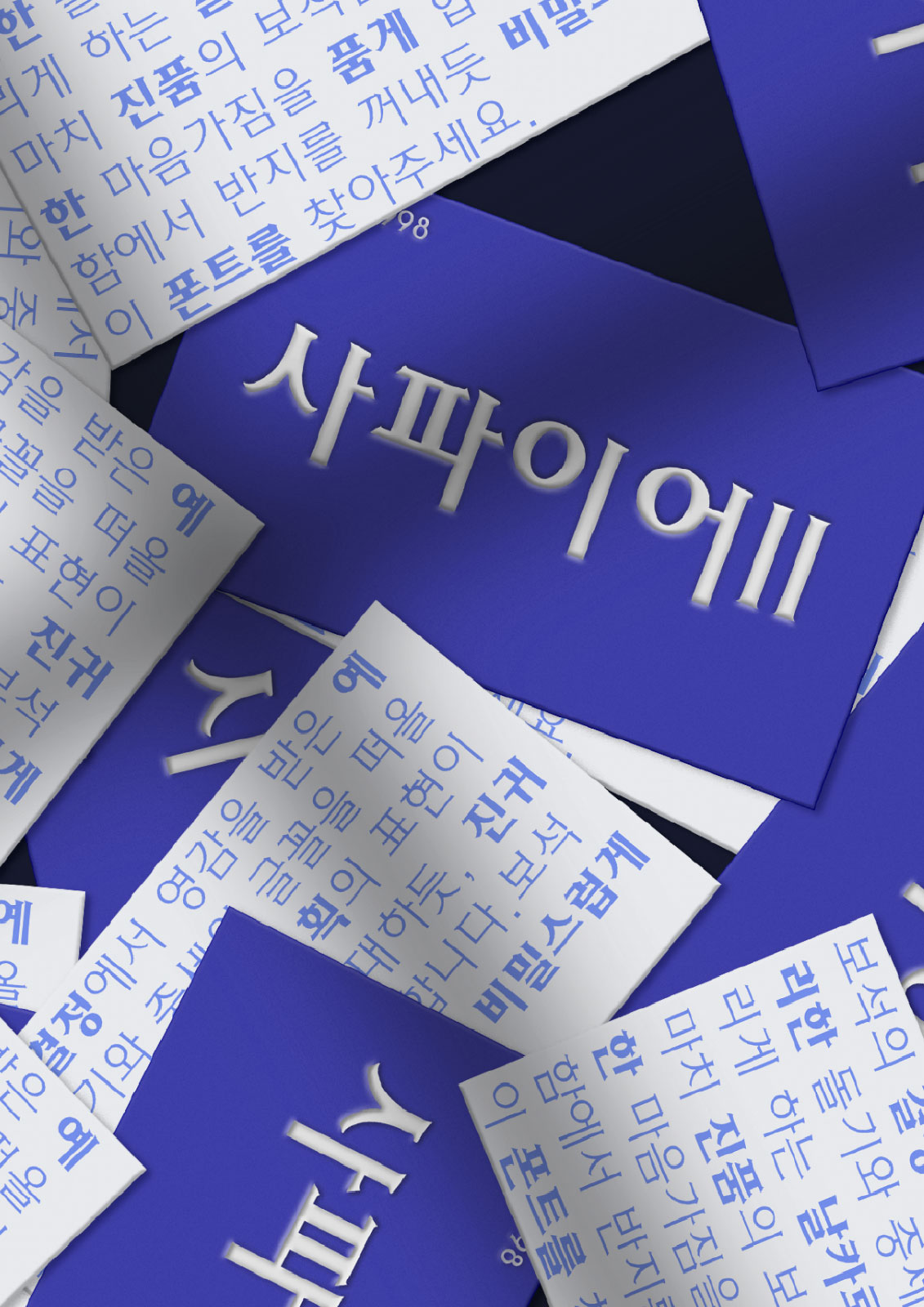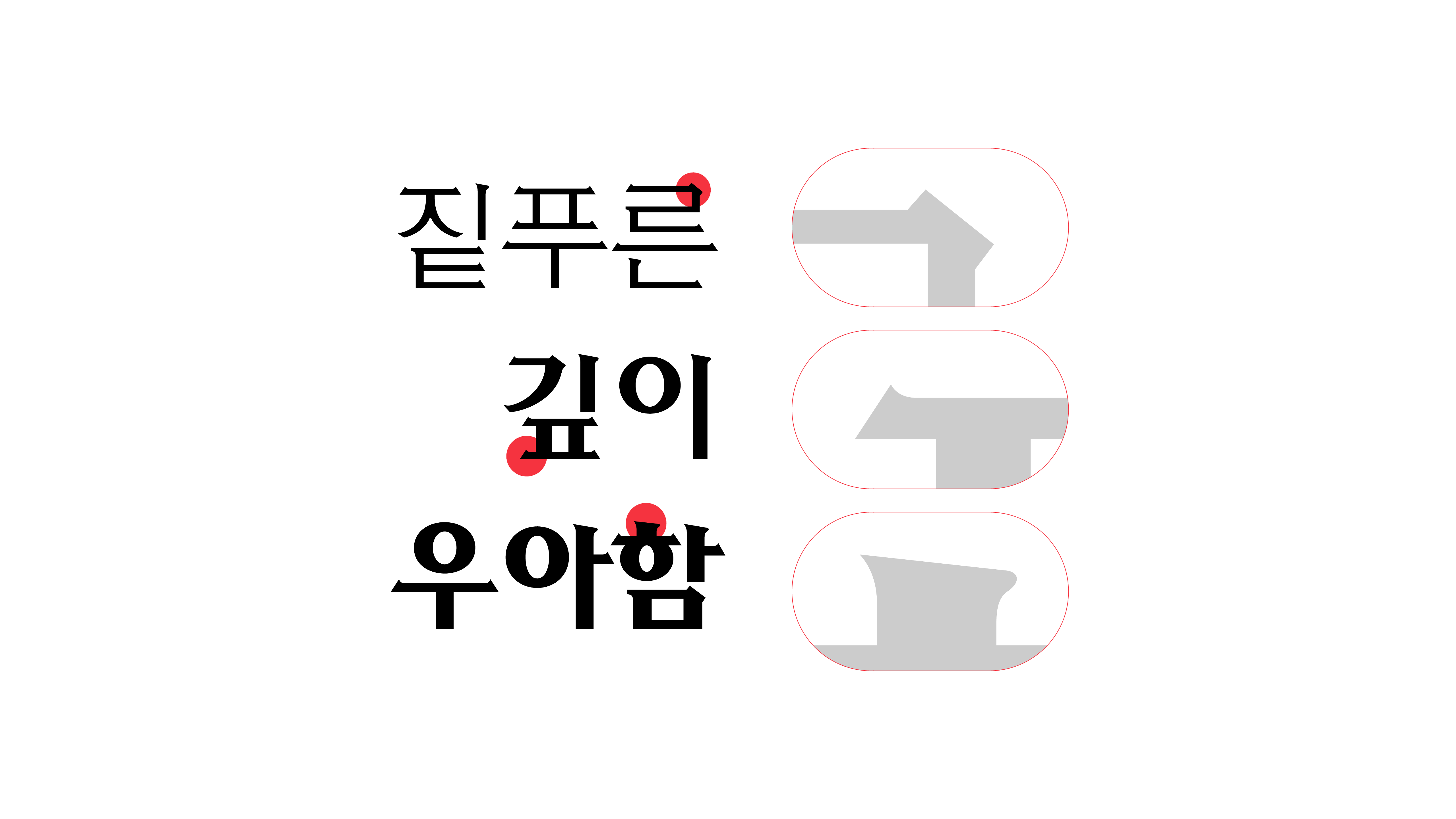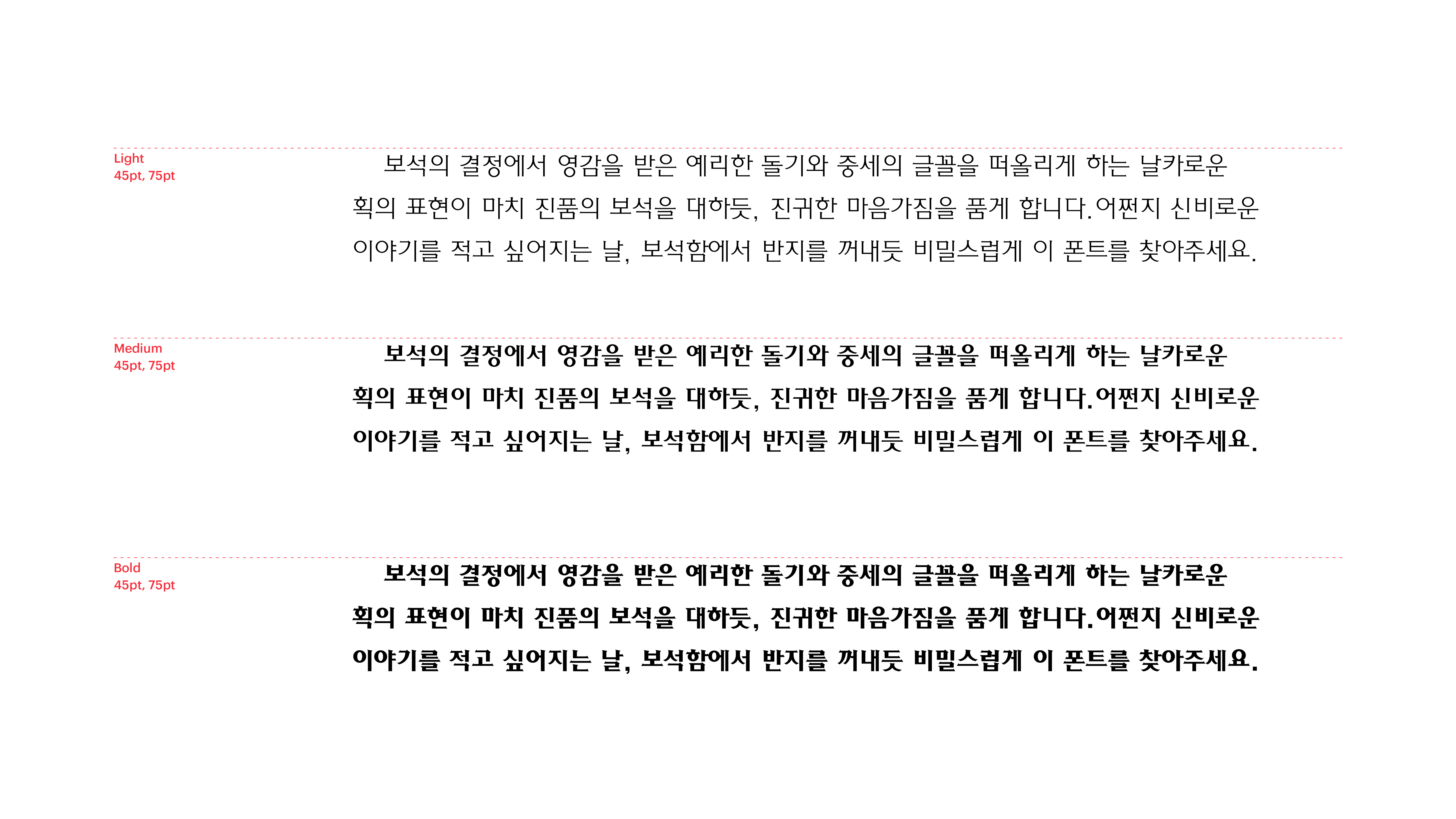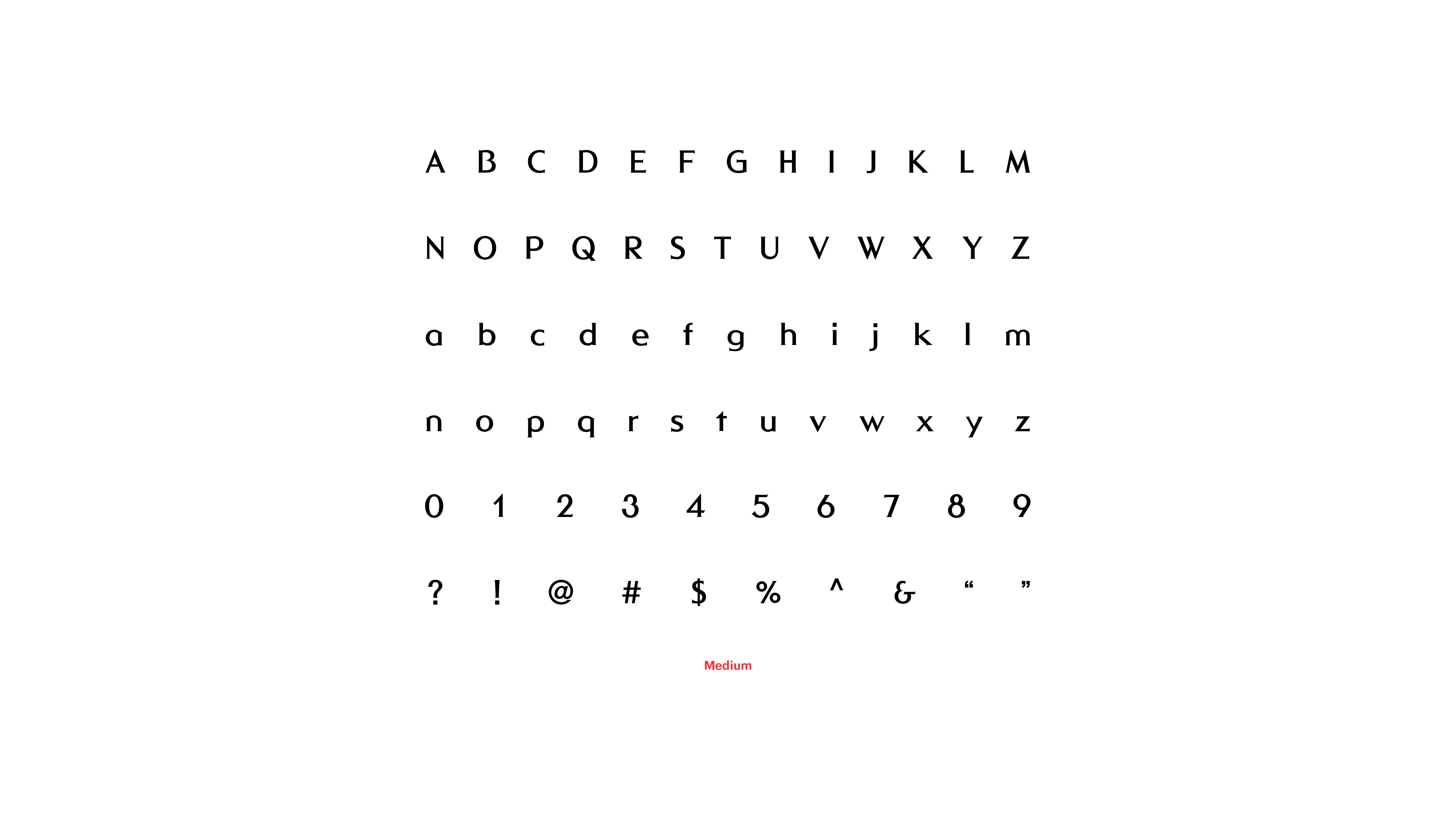
이름만 들어도 짙푸른 신비가 느껴지지 않나요? 사파이어II체는 보석이 품고 있는 깊이와 우아함을 강조한 폰트입니다. 보석의 결정에서 영감을 받은 예리한 돌기와 중세의 글꼴을 떠올리게 하는 날카로운 획의 표현이 마치 진품의 보석을 대하듯, 진귀한 마음가짐을 품게 합니다. 어쩐지 신비로운 이야기를 적고 싶어지는 날, 보석함에서 반지를 꺼내듯 비밀스럽게 이 폰트를 찾아주세요.
Yoon 사파이어II